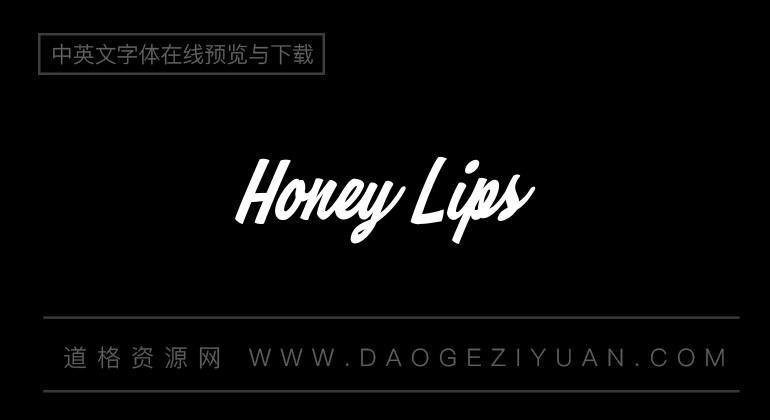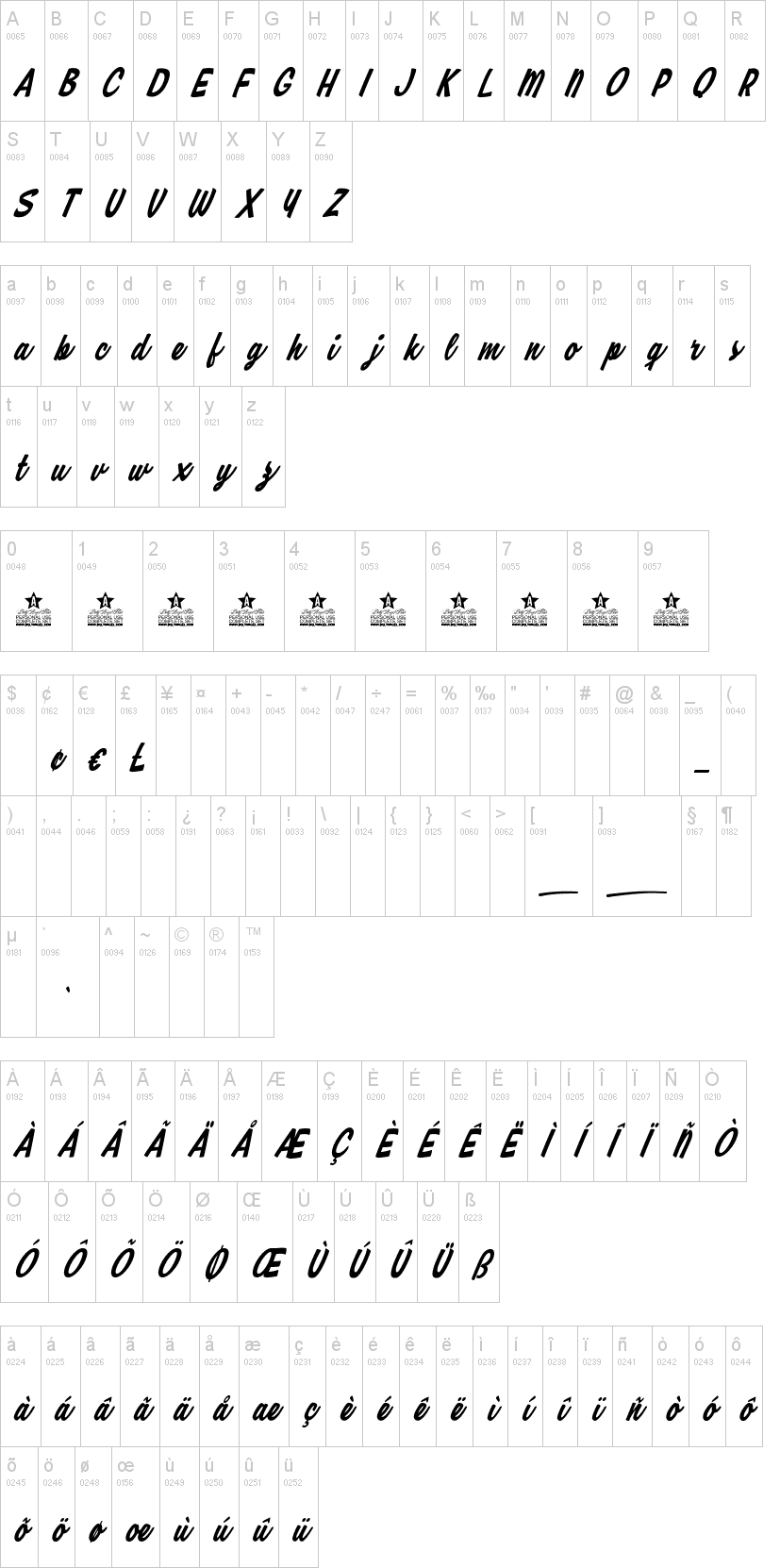
Honey Lips
Honey Lips 是一款比较可爱的脚本字体,它的特点是比较有趣的曲线笔画,带有柔和的气息,而且字母间有着紧密的联系,给人一种温馨的感觉。它可以用于多种场景,例如海报、品牌标志、名片、礼品盒等,能够给作品带来温馨的气息。
Honey Lips是一款非常不错的手写艺术字体,具有很好的视觉感,适合于文化类的宣传设计、商业类品牌的广告和产品包装设计以及个性化文字排版等较多场景。